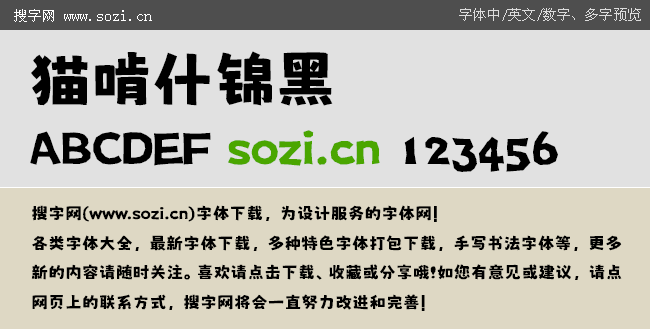
貓啃什錦黑
搜字網(wǎng)給大家提供一款貓啃什錦黑中文字體下載,貓啃什錦黑是一款藝術(shù)黑體字體,是基于日本作者Umihotaru創(chuàng)作的字體Nishiki-teki(日文名:にしき的フォント)進(jìn)行簡體字補(bǔ)充的一款字體。是一款可愛的馬克筆手繪風(fēng)格免費(fèi)商用字體,其筆畫活潑有趣萌萌噠。支持免費(fèi)商用。適合應(yīng)用于藝術(shù)設(shè)計(jì)、平面宣傳設(shè)計(jì)、網(wǎng)頁設(shè)計(jì)、海報(bào)設(shè)計(jì)等應(yīng)用。